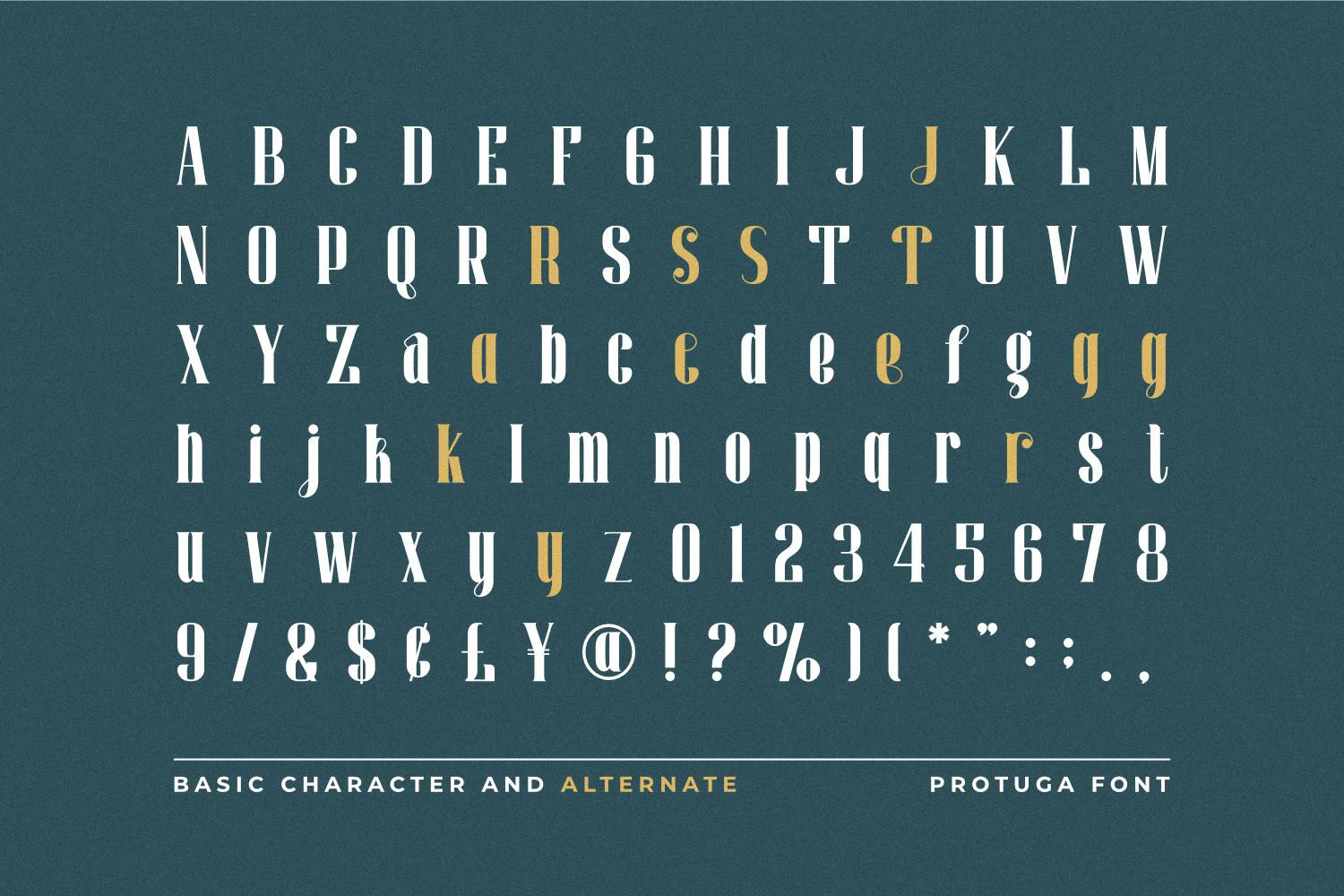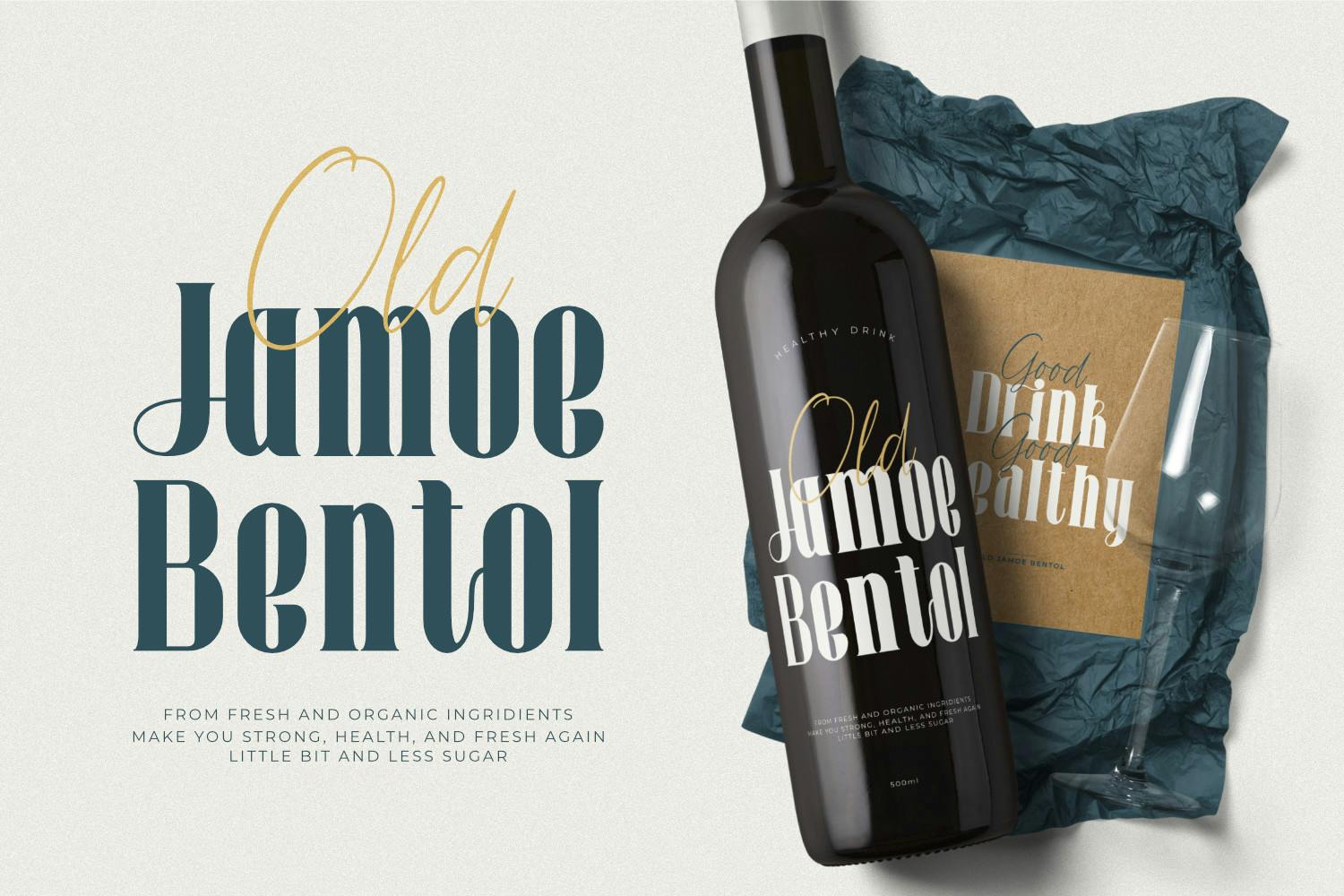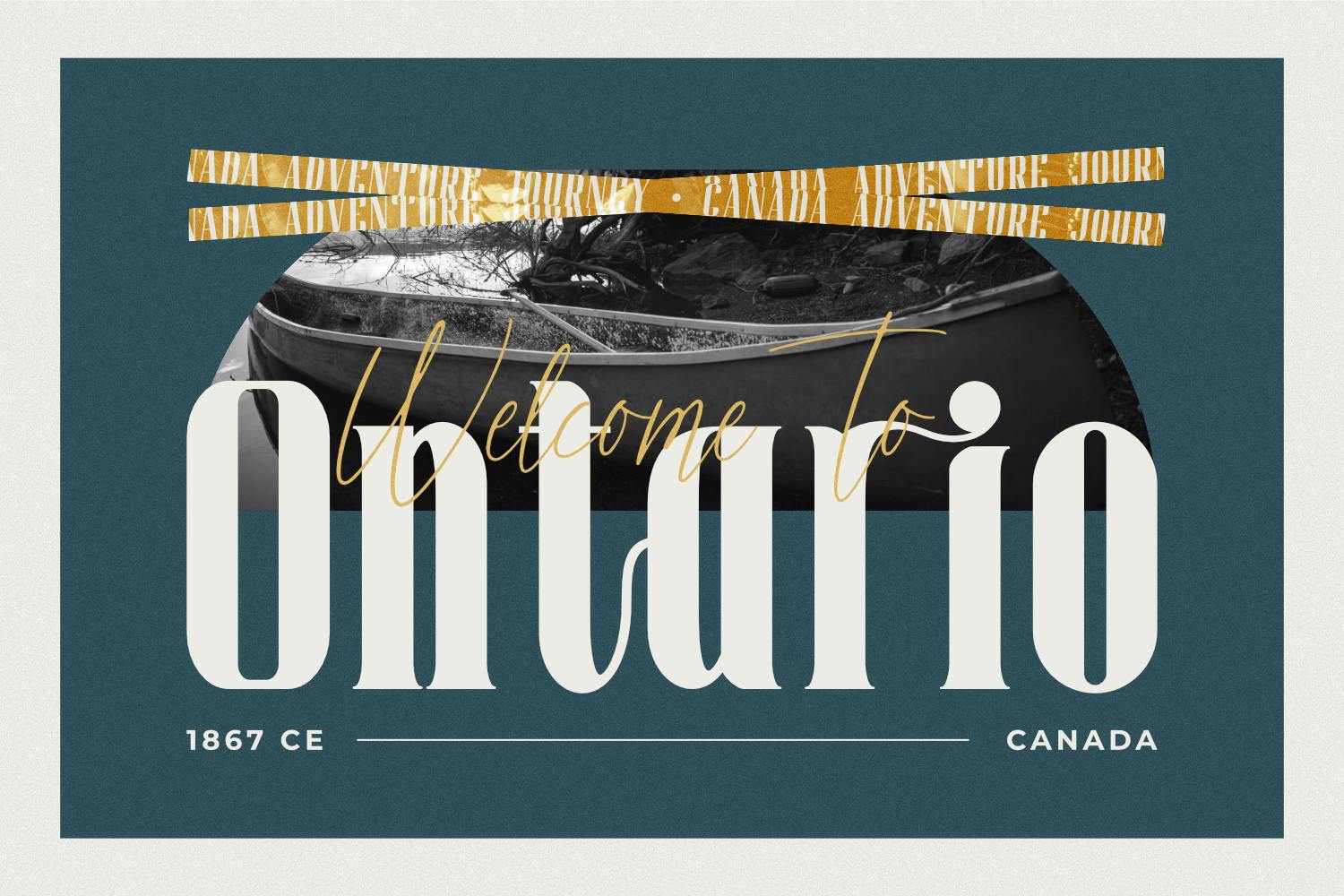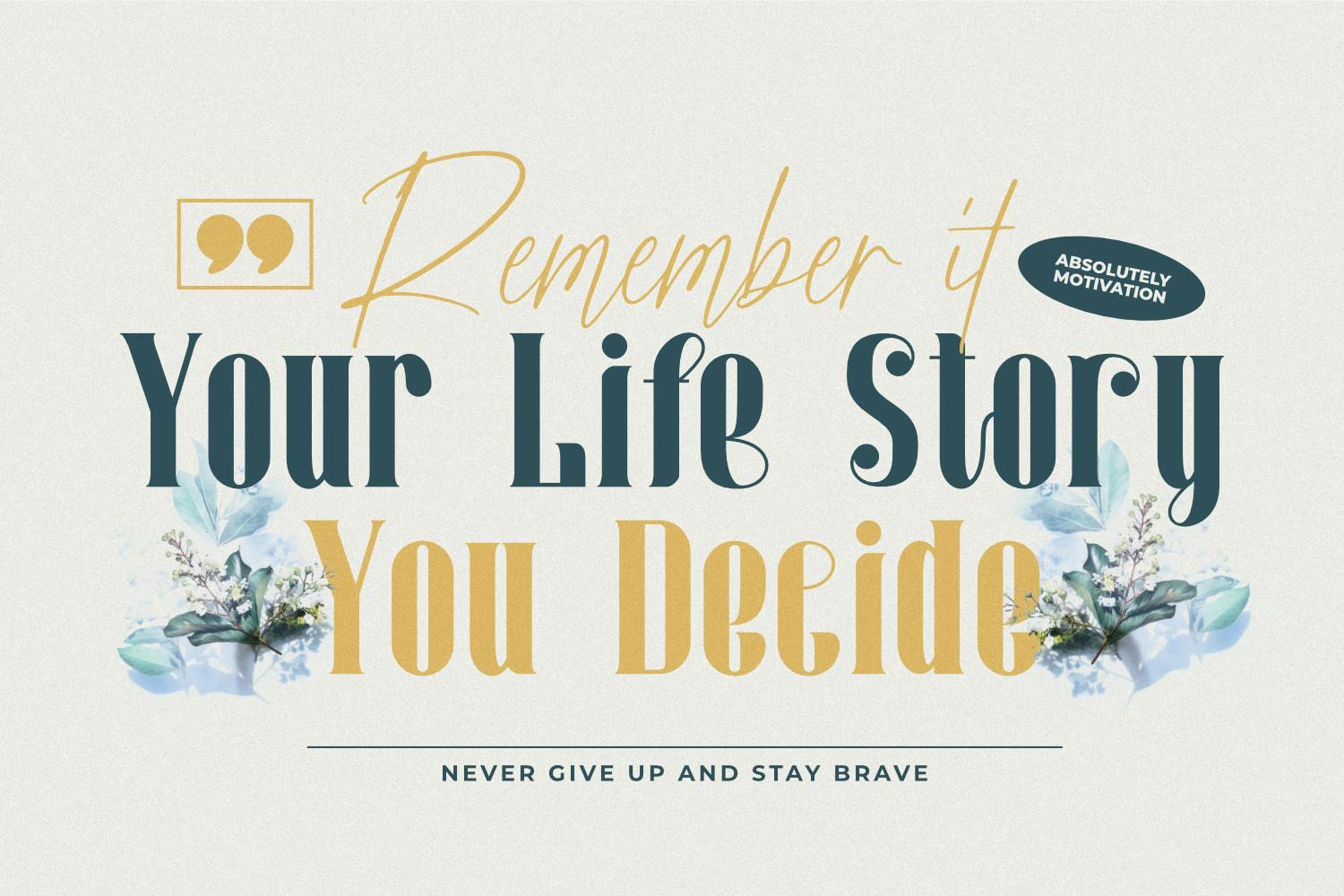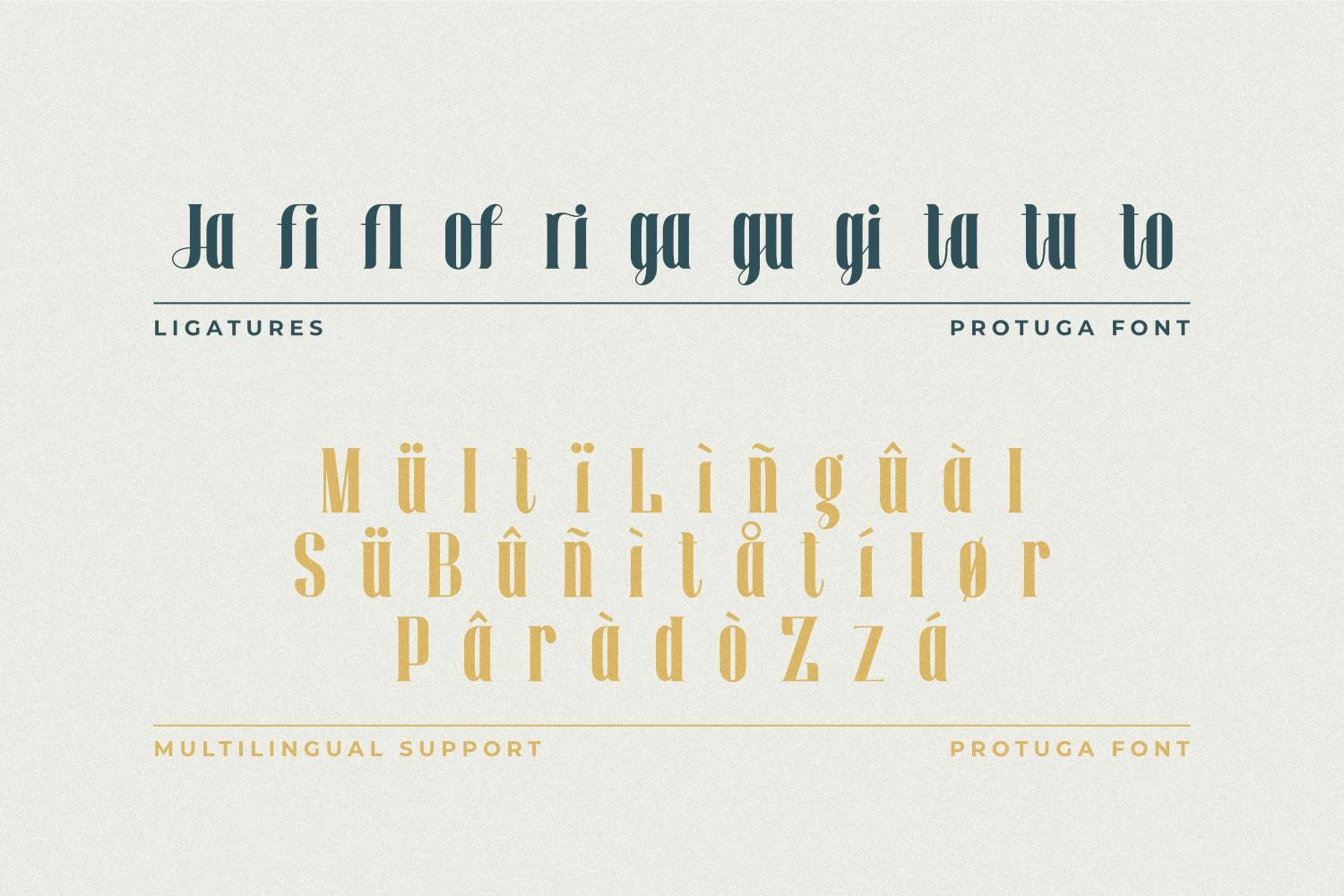
محصول فونت Protuga برای بسیاری از پروژههای شما مناسب است، از جمله طراحی لوگو و برندینگ، عکاسی، دعوتنامهها، واترمارکها، آگهیها، طراحی محصولات، لوازمالتحریر، طراحی عروسی، برچسبها، بستهبندی محصولات، رویدادهای خاص و بسیاری موارد دیگر.